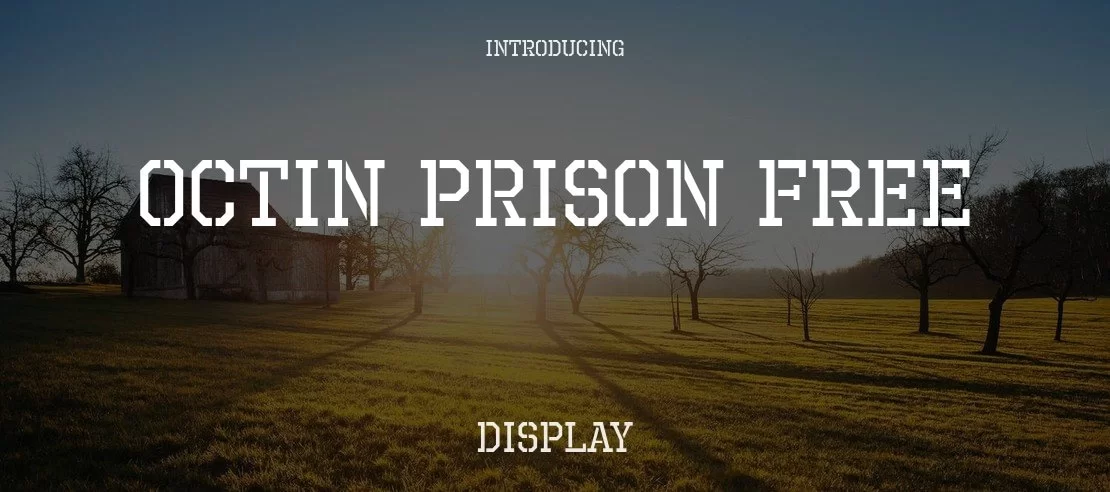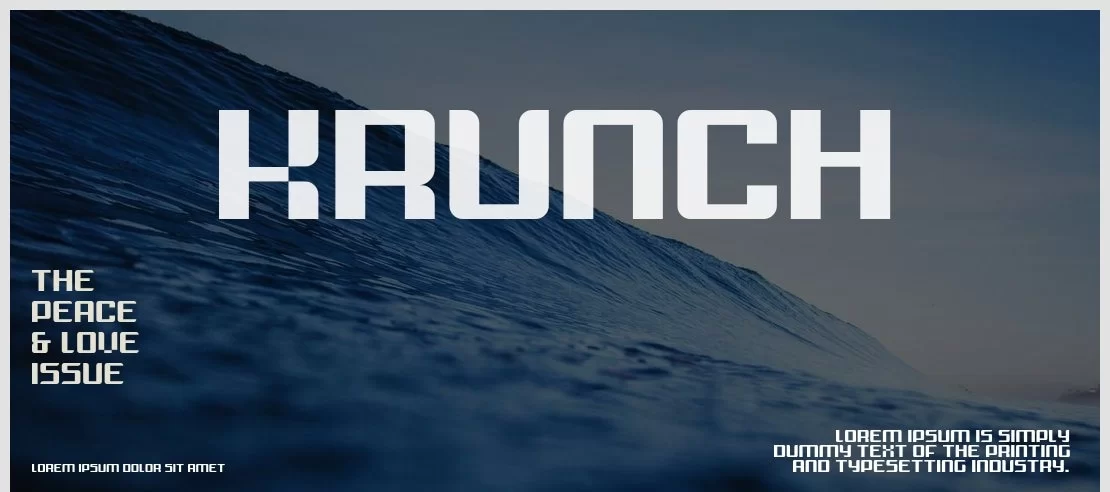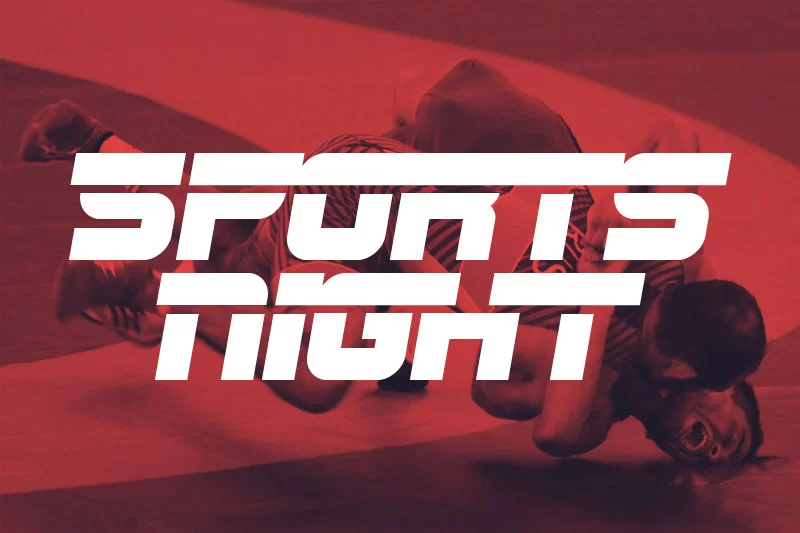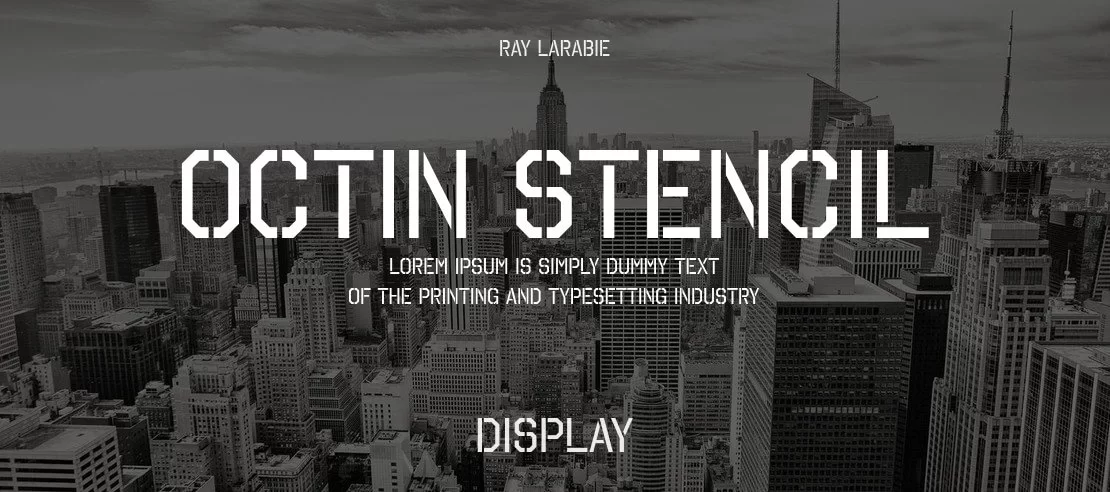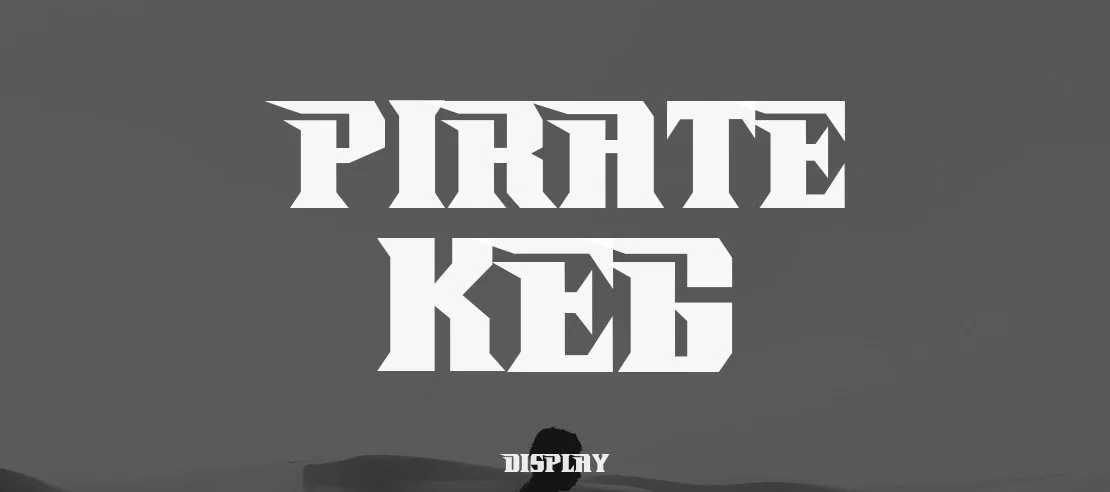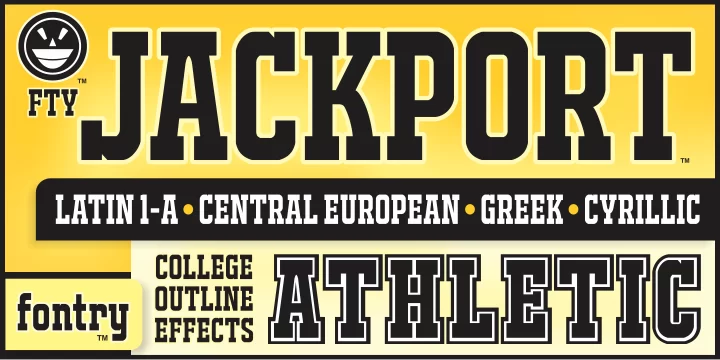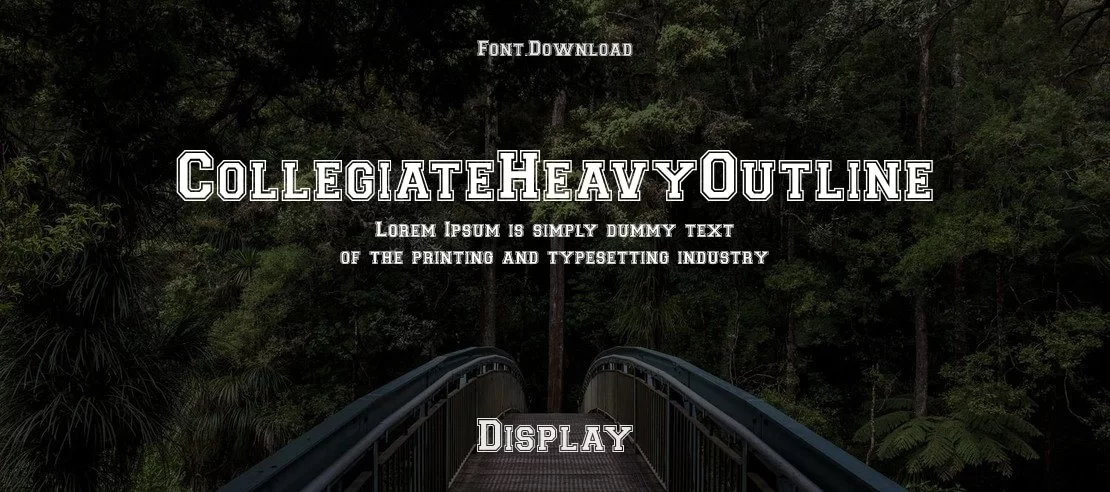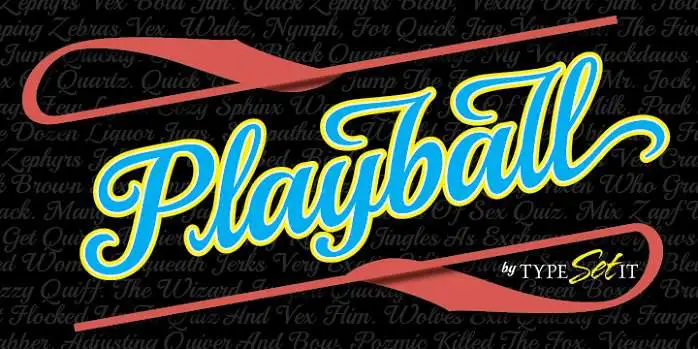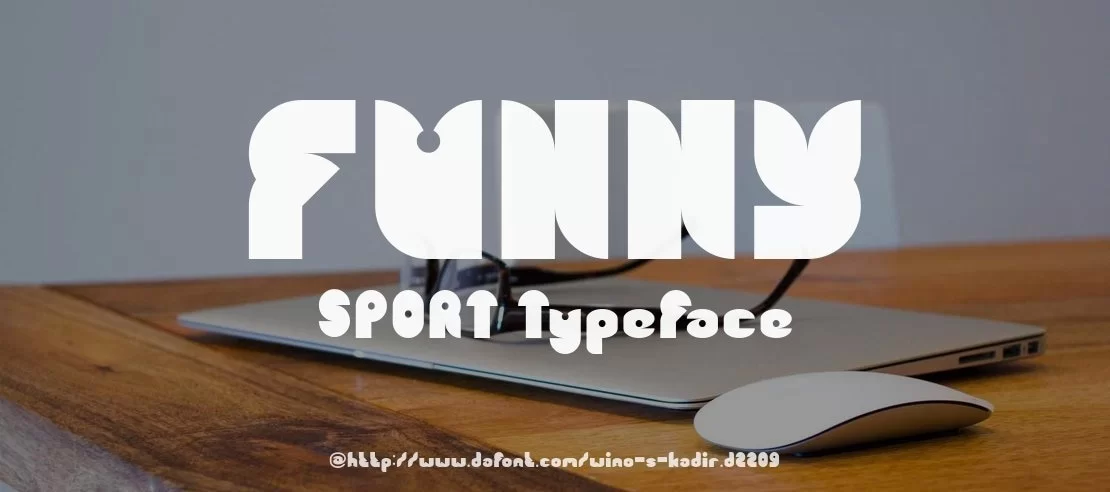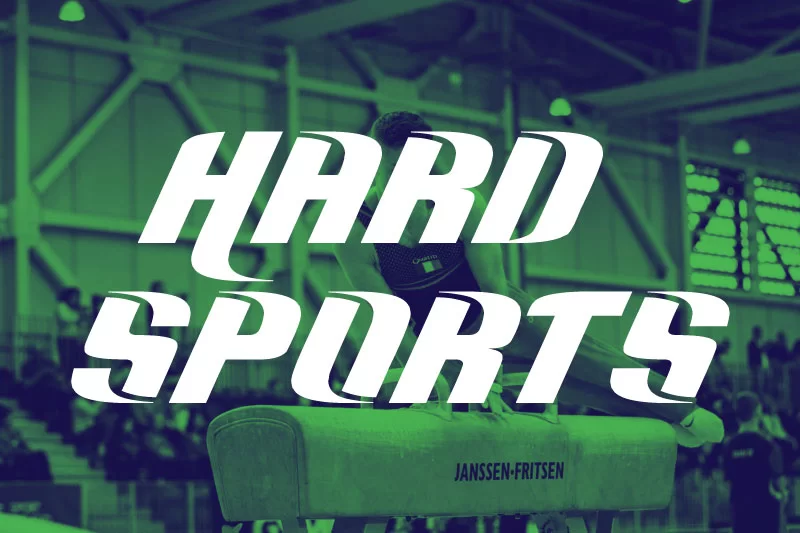
20+ Font chữ thể thao ấn tượng
Các phông chữ thể thao giống nhau và bắt mắt trong thời kỳ retro. Phông chữ Bosox font, sports Cursive fonts, the baseball fonts và Octin sports fonts ảnh hưởng mạnh nhất trong xu hướng retro. Trong bài viết này, mình xin chia sẻ lại các bạn những font chữ thể thao ấn tượng nhất.
DVN Sport Wave​
DVN Sport Wave là một font chữ tuyệt đẹp và cực kỳ phá cách, font chữ này cực kỳ hoàn hảo cho thiết kế Logo với các đường nét uốn lượn và gợn sóng đầy tinh tế.
Không chỉ ứng dụng cho Logo, font chữ này cũng phù hợp cho thiết kế thể thao, banner quảng cáo với hiệu ứng chữ cực kỳ sáng tạo.
DVN Driff Việt hóa​
Hi Jack Việt hóa – Font chữ phong cách thể thao​
DVN Notch tiếng Việt​
DVN Avane Việt hóa​
DVN Revolvingdor Việt hóa​
DVN Avalors Việt hóa​
DVN Avalors Việt hóa là một font chữ hiện đại mang phong cách vượt thời gian, kết hợp giữa sự mạnh mẽ và tính thẩm mỹ tinh tế. Với thiết kế sans-serif đơn giản nhưng ấn tượng, DVN Avalors nổi bật với các đường nét sắc sảo và hình dáng hình học mạnh mẽ. Sự cân đối trong từng chi tiết làm cho font chữ này trở nên lý tưởng cho nhiều loại dự án thiết kế khác nhau, các dự án thể thao, thiết kế Logo,…
DVN Aglet Sans Việt hóa​
Aglet Sans là một font chữ mang đậm phong cách hiện đại và tinh tế, hoàn hảo cho các dự án thiết kế cần sự thanh lịch và rõ ràng. Với các đường nét mềm mại và cân đối, Aglet Sans dễ dàng thu hút ánh nhìn và tạo cảm giác chuyên nghiệp. Đặc điểm nổi bật của font này là khả năng hiển thị rõ ràng trên cả màn hình số và bản in, phù hợp cho nhiều mục đích sử dụng từ thiết kế web, thương hiệu, đến tài liệu quảng cáo.
DVN CYPHER Việt hóa​
DVN CYPHER là một font chữ Việt hóa với phong cách mạnh mẽ và đầy năng động, đặc biệt thích hợp cho các dự án thiết kế liên quan đến lĩnh vực thể thao. Kiểu dáng vuông vức, cứng cáp của font này mang đến cảm giác hiện đại và chuyên nghiệp. Các chi tiết được tinh chỉnh kỹ lưỡng giúp font trở nên dễ đọc nhưng vẫn giữ được sự độc đáo. Với việc hỗ trợ tiếng Việt, DVN CYPHER là lựa chọn hoàn hảo cho các nhà thiết kế muốn tạo ra các bản thiết kế ấn tượng và bắt mắt cho các thương hiệu thể thao, áo đấu, poster sự kiện thể thao, hay các dự án có liên quan đến phong cách mạnh mẽ và tốc độ.
DVN Thể thao – Font chữ thể thao Việt hóa chuyên dụng​
Dựa theo font Bridge Type, font chữ DVN Thể Thao là một lựa chọn nổi bật cho các thiết kế hiện đại và thể thao. Với các nét chữ mạnh mẽ, góc cạnh và đường nét dứt khoát, DVN Thể Thao tạo ra sự ấn tượng mạnh mẽ ngay từ cái nhìn đầu tiên. Kiểu chữ này mang phong cách năng động, phù hợp với các dự án liên quan đến thể thao, giải trí, và công nghệ.
DVN Sports World​
DVN EXPAND Việt hóa​
DVN Sakana Việt hóa​
DVN Nexora Việt hóa​
DVN Revolvingdor Việt hóa​
Hemmet Script Font
Free Octin Prison Sport Font
Free Krunch Font
There are huge numbers of sports fonts available around the world. The Beantown, Cowboys, SF Sports and Mexcellent are few names which belong to recent sport fonts. There are different types of style present in Octin sport fonts. The Octin Stencil, Octin Sports Regular, Octin Stencil Regular and Octin Prison regular are few names of the Octin series of sport fonts.
Sports Night Font
Retro Sports Font
Spliced Regular Font
Fat Bold Sports Font
Athletic Sports Font
Heavy Outline Sport Characters Font
Playball Font Style
Funny Sports Font
Italic Bold Sports Font
Solid Bold Sports Font
Curly Sports Font
Creative Alpha Sports Font